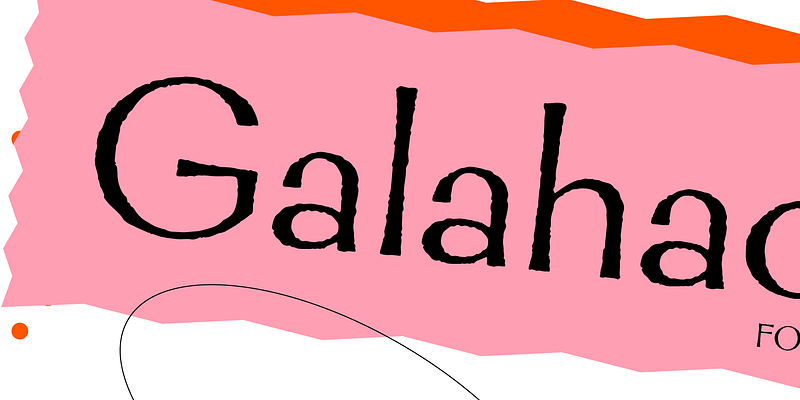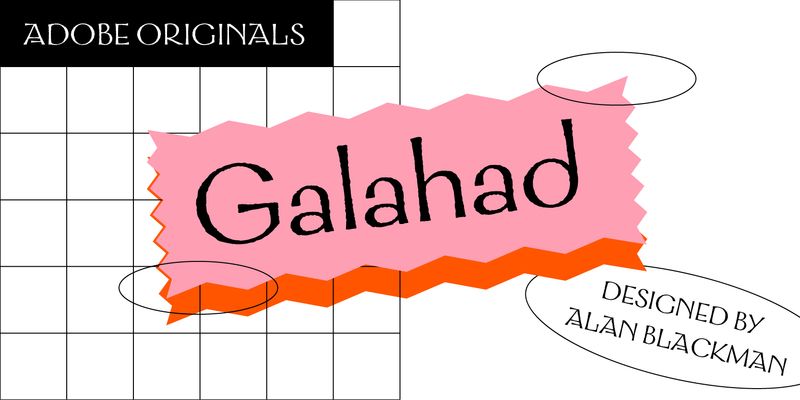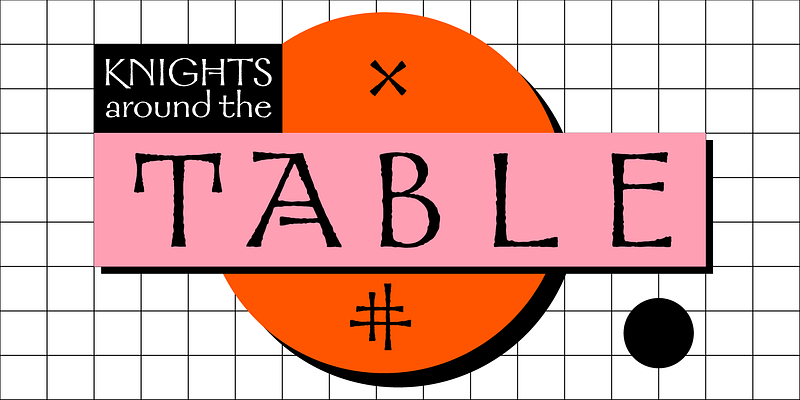
Inspirada en las letras dibujadas a mano por el conocido calígrafo e instructor de letras de San Francisco Alan Blackman, Galahad representa uno de sus estilos característicos. Se han conservado los bordes ásperos y las formas excéntricas de la letra Sans Serif original de Blackman, lo que confiere a los grandes tamaños de cartelería un encanto distintivo y simpático. Describe Galahad (en honor a Sir Galahad, que en la leyenda artúrica buscó y encontró el Santo Grial) como “un cruce entre Optima y la escritura de pluma plana de Friedrich Neugebauer“, el distinguido calígrafo austriaco. Aunque es una Sans Serif de proporciones clásicas, Galahad conserva sus orígenes caligráficos. La inusual A mayúscula es una de las favoritas de Blackman, que la considera su “firma“, ya que añade dramatismo visual al tipo de letra en mayúsculas. Aunque esta adición de 1995 a la biblioteca de Adobe Originals está pensada principalmente para su uso en pantalla, las generosas mayúsculas y las minúsculas abiertas y geométricas hacen que Galahad sea clara y legible en configuraciones de texto informales de hasta 14 puntos.